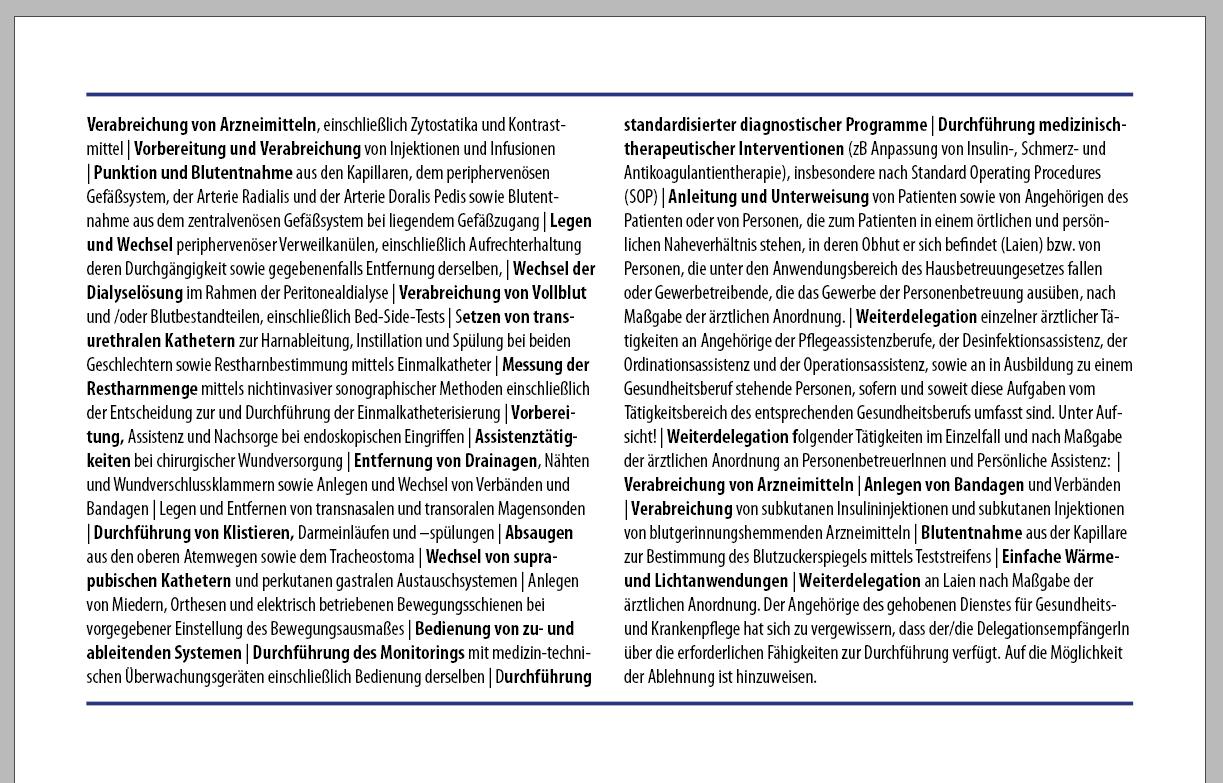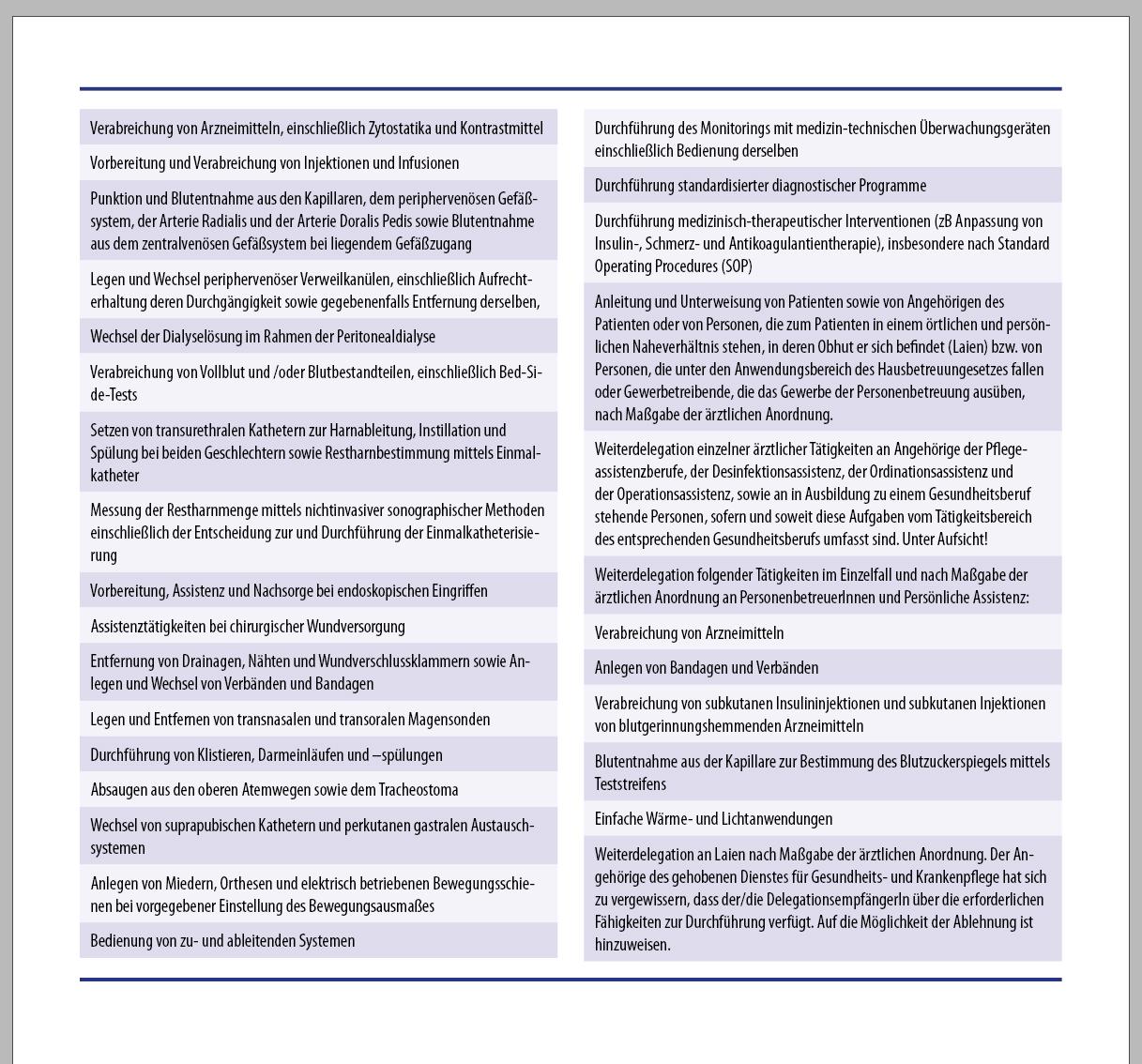
[Mitglied Tage…] Geschrieben Februar 3, 2021 Teilen Geschrieben Februar 3, 2021 Liebes Forum, ich bin auf der Suche nach Gestaltungs-Beispielen für sehr lange Listen. In meinem konkreten Fall geht es um 40 Seiten Fließtext auf A4 in dem in regelmäßigen Abständen Listen vorkommen. Ich möchte nun eine Möglichkeit finden, diese übersichtlicher zu gestalten. Ich habe versucht bei medizinisch-wissenschaftlichen Publikationen fündig zu werden, aber da sind mir bisher leider nicht wirklich gelungene Beispiele untergekommen. Oder würdet ihr eher ganz von einer Auflistung abraten und eine ganz andere Möglichkeit in Betracht ziehen? Liebe Grüße der Tagedieb Beispiel 1: Verabreichung von Arzneimitteln, einschließlich Zytostatika und Kontrastmittel Vorbereitung und Verabreichung von Injektionen und Infusionen Punktion und Blutentnahme aus den Kapillaren, dem periphervenösen Gefäßsystem, der Arterie Radialis und der Arterie Doralis Pedis sowie Blutentnahme aus dem zentralvenösen Gefäßsystem bei liegendem Gefäßzugang Legen und Wechsel periphervenöser Verweilkanülen, einschließlich Aufrechterhaltung deren Durchgängigkeit sowie gegebenenfalls Entfernung derselben, Wechsel der Dialyselösung im Rahmen der Peritonealdialyse Verabreichung von Vollblut und /oder Blutbestandteilen, einschließlich Bed-Side-Tests Setzen von transurethralen Kathetern zur Harnableitung, Instillation und Spülung bei beiden Geschlechtern sowie Restharnbestimmung mittels Einmalkatheter Messung der Restharnmenge mittels nichtinvasiver sonographischer Methoden einschließlich der Entscheidung zur und Durchführung der Einmalkatheterisierung Vorbereitung, Assistenz und Nachsorge bei endoskopischen Eingriffen Assistenztätigkeiten bei chirurgischer Wundversorgung Entfernung von Drainagen, Nähten und Wundverschlussklammern sowie Anlegen und Wechsel von Verbänden und Bandagen Legen und Entfernen von transnasalen und transoralen Magensonden Durchführung von Klistieren, Darmeinläufen und –spülungen Absaugen aus den oberen Atemwegen sowie dem Tracheostoma Wechsel von suprapubischen Kathetern und perkutanen gastralen Austauschsystemen Anlegen von Miedern, Orthesen und elektrisch betriebenen Bewegungsschienen bei vorgegebener Einstellung des Bewegungsausmaßes Bedienung von zu- und ableitenden Systemen Durchführung des Monitorings mit medizin-technischen Überwachungsgeräten einschließlich Bedienung derselben Durchführung standardisierter diagnostischer Programme Durchführung medizinisch-therapeutischer Interventionen (zB Anpassung von Insulin-, Schmerz- und Antikoagulantientherapie), insbesondere nach Standard Operating Procedures (SOP) Anleitung und Unterweisung von Patienten sowie von Angehörigen des Patienten oder von Personen, die zum Patienten in einem örtlichen und persönlichen Naheverhältnis stehen, in deren Obhut er sich befindet (Laien) bzw. von Personen, die unter den Anwendungsbereich des Hausbetreuungesetzes fallen oder Gewerbetreibende, die das Gewerbe der Personenbetreuung ausüben, nach Maßgabe der ärztlichen Anordnung. Weiterdelegation einzelner ärztlicher Tätigkeiten an Angehörige der Pflegeassistenzberufe, der Desinfektionsassistenz, der Ordinationsassistenz und der Operationsassistenz, sowie an in Ausbildung zu einem Gesundheitsberuf stehende Personen, sofern und soweit diese Aufgaben vom Tätigkeitsbereich des entsprechenden Gesundheitsberufs umfasst sind. Unter Aufsicht! Weiterdelegation folgender Tätigkeiten im Einzelfall und nach Maßgabe der ärztlichen Anordnung an PersonenbetreuerInnen und Persönliche Assistenz: Verabreichung von Arzneimitteln Anlegen von Bandagen und Verbänden Verabreichung von subkutanen Insulininjektionen und subkutanen Injektionen von blutgerinnungshemmenden Arzneimitteln Blutentnahme aus der Kapillare zur Bestimmung des Blutzuckerspiegels mittels Teststreifens Einfache Wärme- und Lichtanwendungen Weiterdelegation an Laien nach Maßgabe der ärztlichen Anordnung. Der Angehörige des gehobenen Dienstes für Gesundheits- und Krankenpflege hat sich zu vergewissern, dass der/die DelegationsempfängerIn über die erforderlichen Fähigkeiten zur Durchführung verfügt. Auf die Möglichkeit der Ablehnung ist hinzuweisen. Link zu diesem Kommentar
[Mitglied Mart…] Geschrieben Februar 3, 2021 Teilen Geschrieben Februar 3, 2021 So ganz wirst Du Auflistungen wohl in der Praxis nicht vermeiden können. Sinnvoll und lesefreundlich kann eine Unterteilung mit Zwischenüberschriften sein. Oder — gegebenenfalls — Auflistungsebenen zu nutzen. Das ist allerdings eher eine redaktionelle Anforderung. Ebenso wäre es eine Variante, vor jeden Listenpunkt ein einzelnes gefettetes Wort zu setzen, dass den Punkt – wenn nicht zusammenfasst, so doch kategorisiert. Aus typografischer Sicht würde ich auch empfehlen, bei dem Format A4 diese Listen zweispaltig zu setzen, damit die Listenpunkte (die ja im Hackbrettstil formuliert sind) noch halbwegs angenehm zu lesen sind. Link zu diesem Kommentar
[Mitglied Juli…] Geschrieben Februar 3, 2021 Teilen Geschrieben Februar 3, 2021 Gibt es die Möglichkeit einer Ordnung, alphabetisch oder nach Themen? Dann: Zwischenüberschriften nach Thema/Gruppierung oder Anfangsbuchstabe Fettungen entweder in Form von Spitzmarken (notfalls Phrasen) oder dem Hauptthema des Absatzes? Das alles ist jedoch sehr auf den Einzelfall bezogen und funktioniert nur, wenn es auch thematisch sinnvoll ist. Und: Werden die Untergliederungsmöglichkeiten nicht optimal und sparsam eingesetzt, tragen sie nur zusätzlich zu weiterer Verwirrung bei. 1 Link zu diesem Kommentar
[Mitglied Eckh…] Geschrieben Februar 3, 2021 Teilen Geschrieben Februar 3, 2021 Es wäre gut zu wissen, was diese Liste bedeutet. Sind das zu erbringende Leistungen? Müssen die übersichtlich dargestellt sein? Das frage ich jetzt allen ernstes, denn es gibt eine Menge solcher Listen, die eigentlich kein Mensch anschaut aber irgednwie dort stehen müssen. In solchen Fällen habe ich schon mal lange Aufzählungen einfach hintereinandergeklatscht. Vielleicht mit einem Trennzeichen dazwischen und einem markanten und fett gesetzten Anfangswort (siehe Martin). Ich mag ja immer noch den | -Strich als Trenner. Ansonsten bieten sich auch einen Tabelle ohne Linien mit abwechselndne Hintergundflächen an, das erhöht die Orientierung. Auf DIN A4 zweispaltig, wie Martin Schulz das meinte, ist da sicher ein guter Ratschlag. Meine persönliche Meinung: Fast alles ist besser als Aufzählungen mit einem Punkt davor. 1 Link zu diesem Kommentar
[Mitglied 681a…] Geschrieben Februar 3, 2021 Teilen Geschrieben Februar 3, 2021 Nur ein Gedanke: Die Listen mit einem Condensed-Schnitt (hier aus der PT-Familie) zweispaltig setzen spart unglaublich viel Platz. Link zu diesem Kommentar
[Mitglied Eckh…] Geschrieben Februar 3, 2021 Teilen Geschrieben Februar 3, 2021 Wenn bertel fleißig ist, will ich das auch sein und meinen Tabellenvorschlag visualisieren. Hier mit Myriad condensed 10 pt. Zweispaltig auf DIN A4. 3 Link zu diesem Kommentar
[Mitglied Eckh…] Geschrieben Februar 3, 2021 Teilen Geschrieben Februar 3, 2021 Und die Version: "Mich liest eh keiner, ich bin das Kleingedruckte" 4 Link zu diesem Kommentar